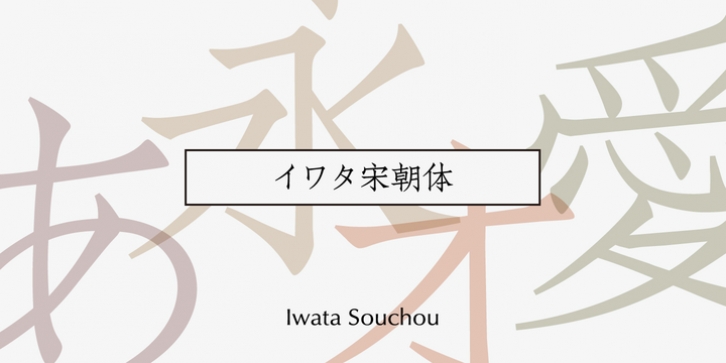
Iwata Souchou Pro was published by IWATA. Iwata Souchou Pro contains 1 style.
金属活å—ã®ã€Œæ–¹å®‹ä½“ã€ã‚’ã‚‚ã¨ã«é–‹ç™ºã—ãŸæ›¸ä½“ã§ã™ã€‚æ´»å—æ™‚ä»£ã®æ¼¢å—ã€ä»®å—ã‚’å†ç¾ã—ãŸã€Œå®‹æœä½“ã€ã¨ã€ä»®å—デザインをç¾ä»£é¢¨ã«ã‚¢ãƒ¬ãƒ³ã‚¸ã—ãŸã€Œå®‹æœä½“æ–°ãŒãªã€ã®2書体ãŒã‚りã¾ã™ã€‚